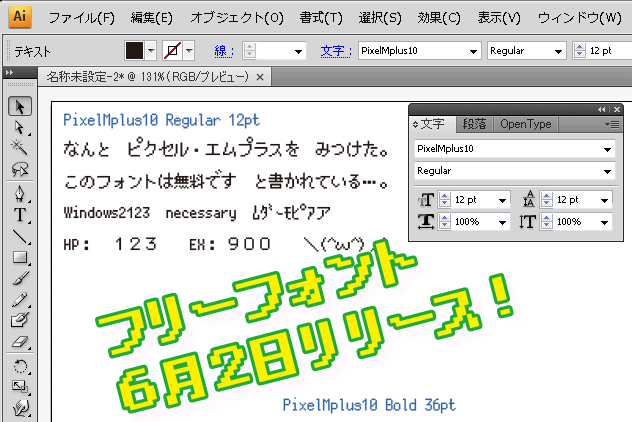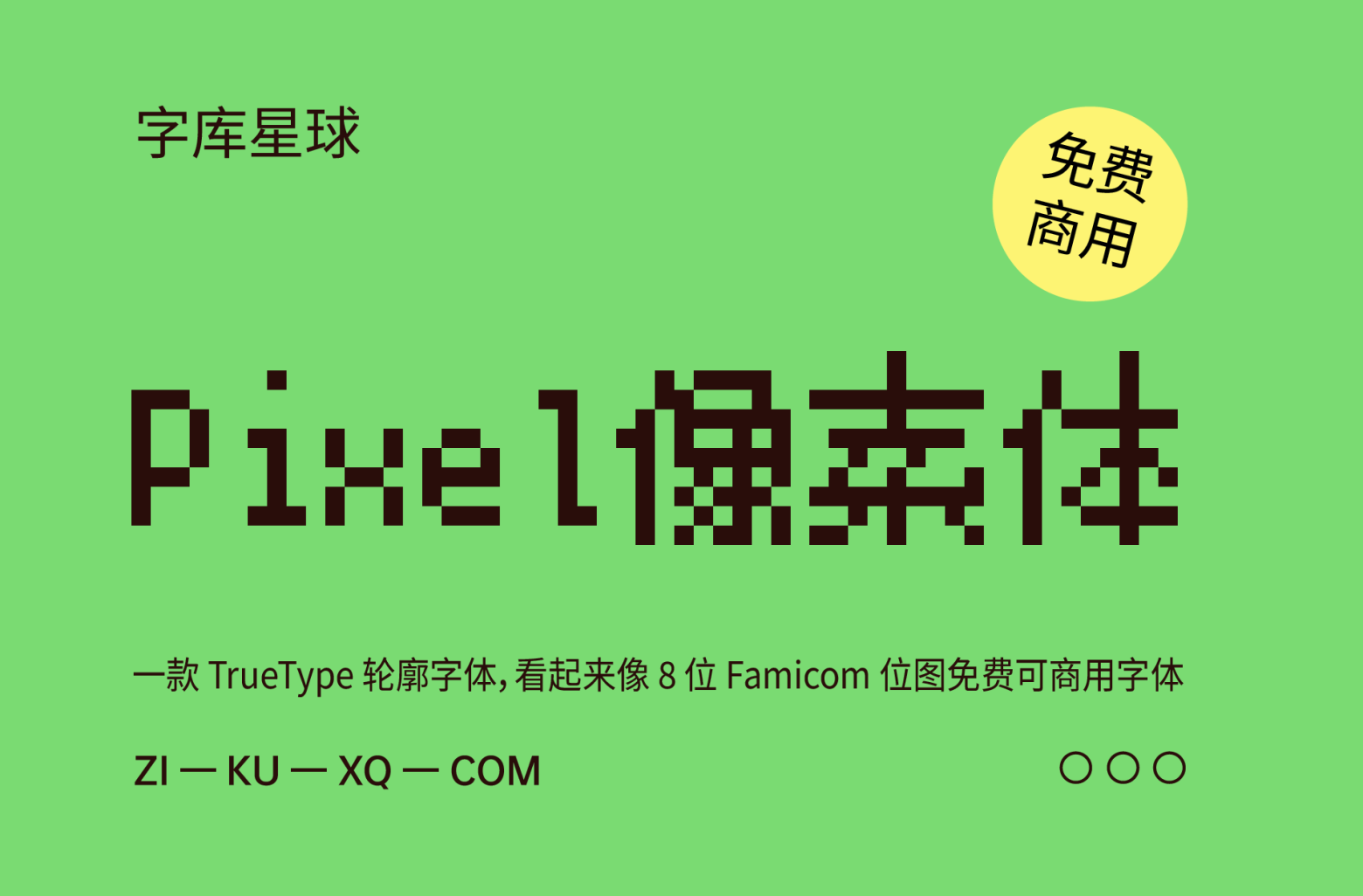
Pixel像素体
Pixel像素体(PixelMplus)是一款 TrueType 轮廓字体,看起来像 8 位 Famicom 位图免费可商用字体。
Pixel像素体
JIS收录了第1、第2水平的所有汉字。ISO-8859-1(Latin-1)的文字也收录。除此之外还追加了几个记号。
实体只是单纯的TrueType等宽字体。也可以在文本编辑器中使用。